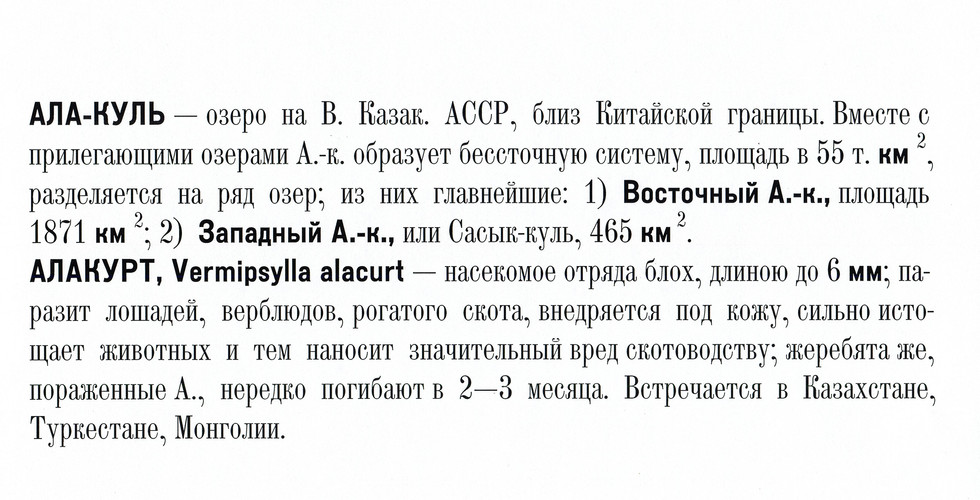
Линотипная шрифтовая пара Обыкновенный узкий и Гротеск узкий.
В разработке шрифтовая пара DXOldStandardCondensed/DXOldStandardGrotesk - цифровая версия линотипных шрифтов Обыкновенный узкий и Гротеск узкий. Пара использовалась для набора технической литературы и справочников с конца XIX века. Выпускалась в 9 и 10 кеглях.